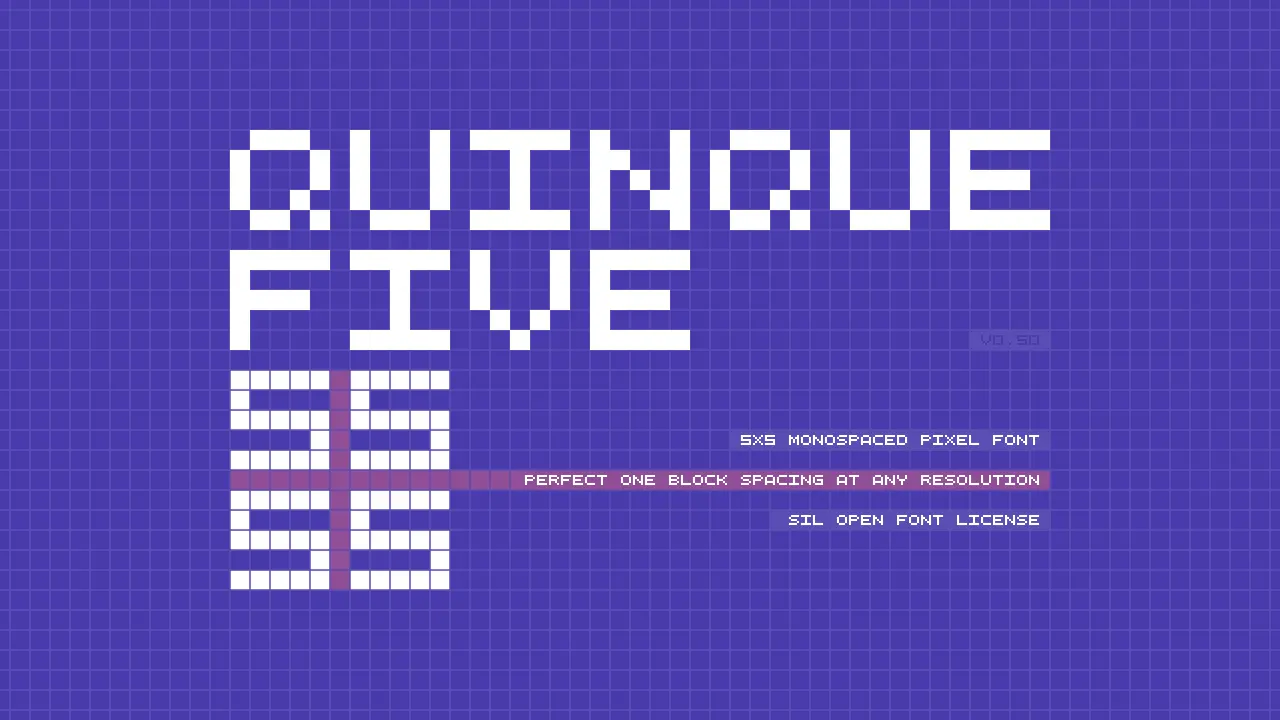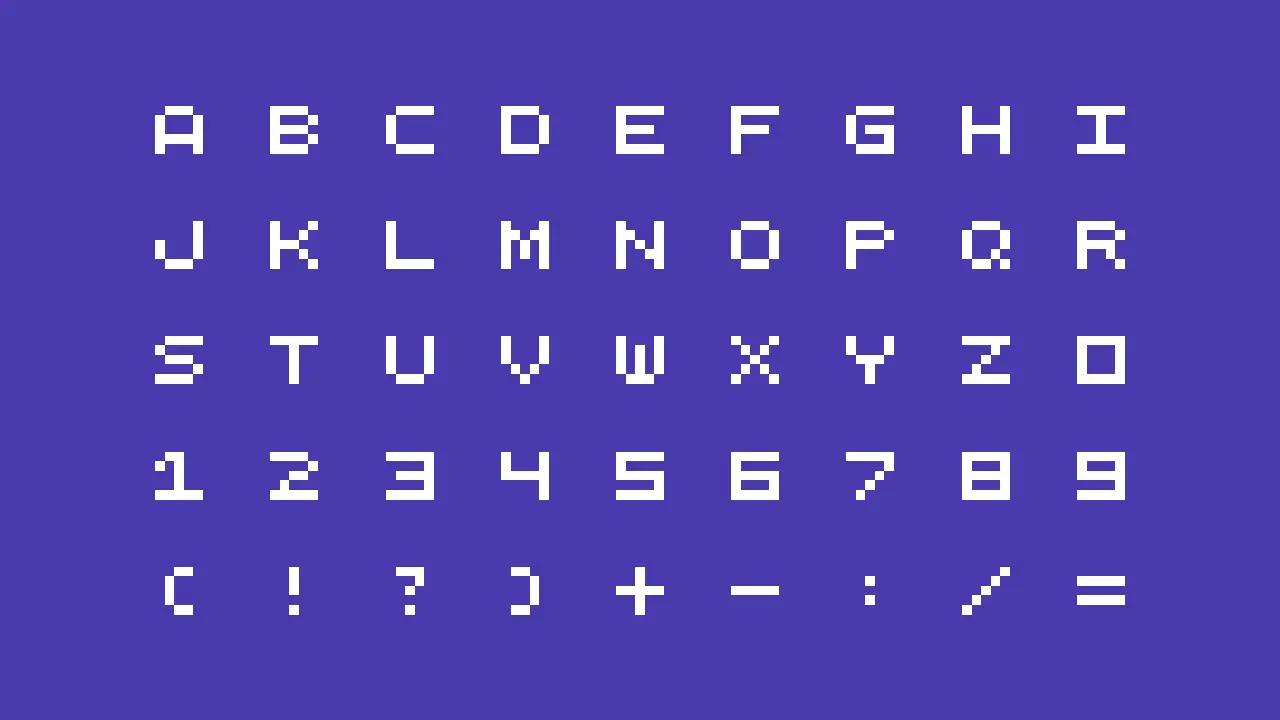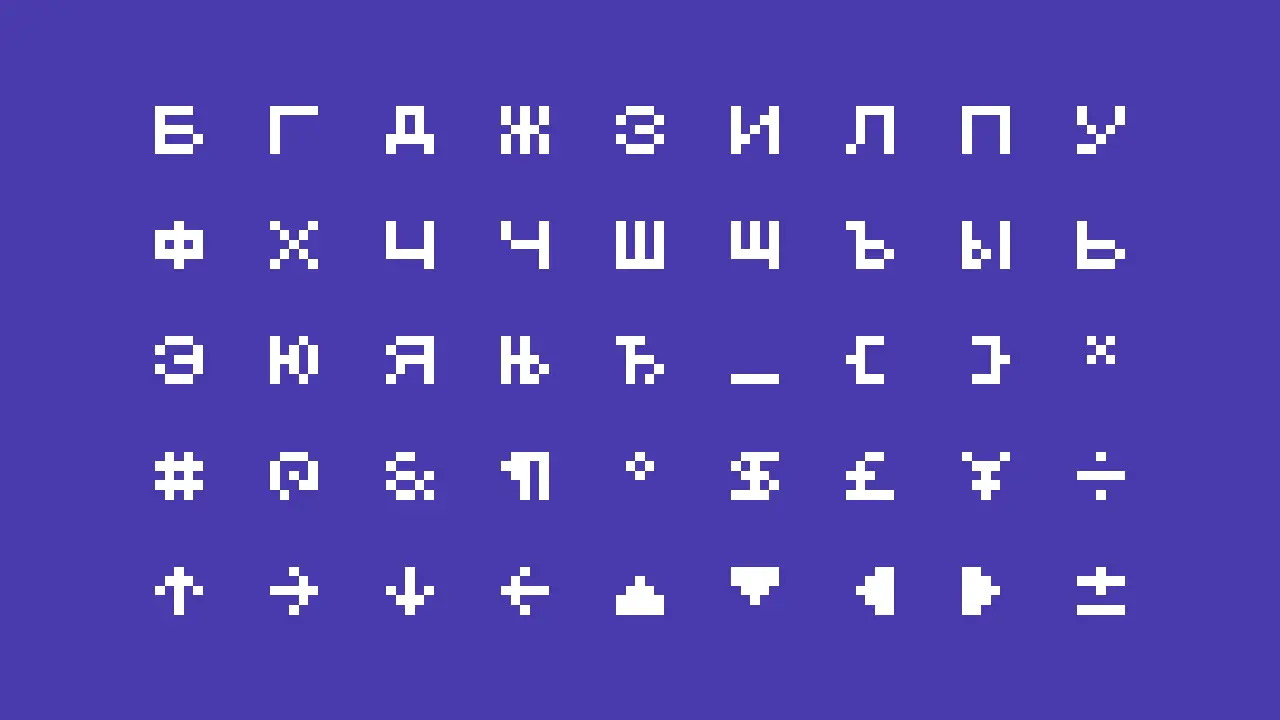
QuinqueFive介紹
QuinqueFive一款根據SIL OFL協議發佈的免費英文字體,5x5等寬像素字體, 字體包含 540 個字形。
推薦的字體設置:僅以 5px/4pt 的倍數使用它,並關閉抗鋸齒。
支持 39 種語言(Asu、Bemba、Bena、波斯尼亞語、保加利亞語、車臣語、Chiga、康沃爾語、英語、Gusii、印度尼西亞語、Kalenjin、Kinyarwanda、Luyia、Machame、Makhuwa-Meetto、Makonde、Morisyen、North Ndebele、Nyankole、Oromo、Rombo、Rundi 、俄語、盧瓦語、桑布魯語、桑古語、塞爾維亞語、香巴拉語、紹納語、索加語、索馬里語、斯瓦希里語、泰塔語、特索語、烏茲別克語(拉丁語)、文喬語、祖魯語。)